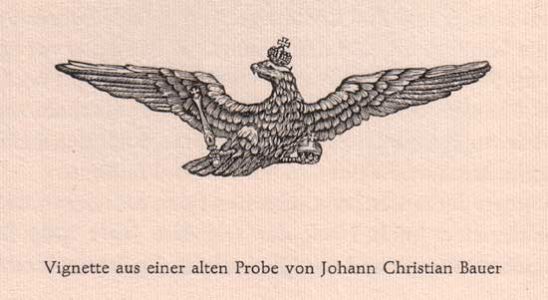
Logo Bauersche Gießerei gesucht
Ich brauche für meine Webseite ein Logo der Bauerschen Gießerei. Es sollte auf 50 x 50 Pixel gebracht werden können.
Ich meine dieses Logo mit der Windrose.
Kann mir da vielleicht jemand helfen?
Aber ich dachte, es gäbe das alte Logo der Bauerschen irgendwo,
nicht das der Typo Bauer, Barcelona.
In „Werden und Wachsen einer deutschen Schriftgießerei“
(Ausgabe zum hundertjährigen Bestehen der Bauerschen Gießerei) habe ich das Logo nicht gefunden,
auch nicht im Schriftmuster zur Manuskript Gotisch. Leider!
Dafür ist mit die Vignette aus einer alten Probe von Johann Christian Bauer
(-> der Adler, den Du in einem anderen Thema gezeigt hast)
„über den Weg gelaufen“.
Ist schon wahr: Immer an der Quelle bleiben.
Der Adler ist aus einem Schriftmusterbuch von Klinkhardt von 1908.
Man muß da unterscheiden.
Das hier ist der Adler des Königreich Preußen:
Und das hier ist der Adler des Deutschen Reiches:
In den alten Schriftmuster-Büchern wird das auch fein säuberlich getrennt. Der Kaiser-Adler gefiel mir rein optisch besser. Auch, wenn ich den letzten Kaiser aufgrund der bekannten Vorkommnisse natürlich ablehne.
Das spiegelt sich übrigens auch bei den Schmuck-Vignetten wider. Die der Kaiserzeit sind viel barocker:
Übrigens habe ich mehr durch Zufall den Bericht der Schriftgießerei Stempel zur Tannenberg u.a. "neu-gotischen" Schriten in die Hände bekommen. Aus dem Fachmagazin "Graphische Nachrichten" von Juli 1937.
Natürlich kann man den preußischen Adler nicht mit dem Reichsadler gleichsetzen.
Das widerspräche vollkommen der Geschichte des Heiligen Römischen Reiches,
die lange Zeit von Kaisern aus Österreich-Ungarn bestimmt wurde.
Mir ging es nur um die Urheberschaft der Vignette! Mein Fund:
Au Mann, ist der schön.
Das Heft hat ein Format 23 cm x 33 cm.
Der Bericht heißt:
Vom Schriftschaffen
der Schriftgießerei D.Stempel AG, Frankfurt am Main
und geht über 8 Seiten.
Herr Hartmann von Bauer Types in Barcelona hat es mir zur Verfügung gestellt.